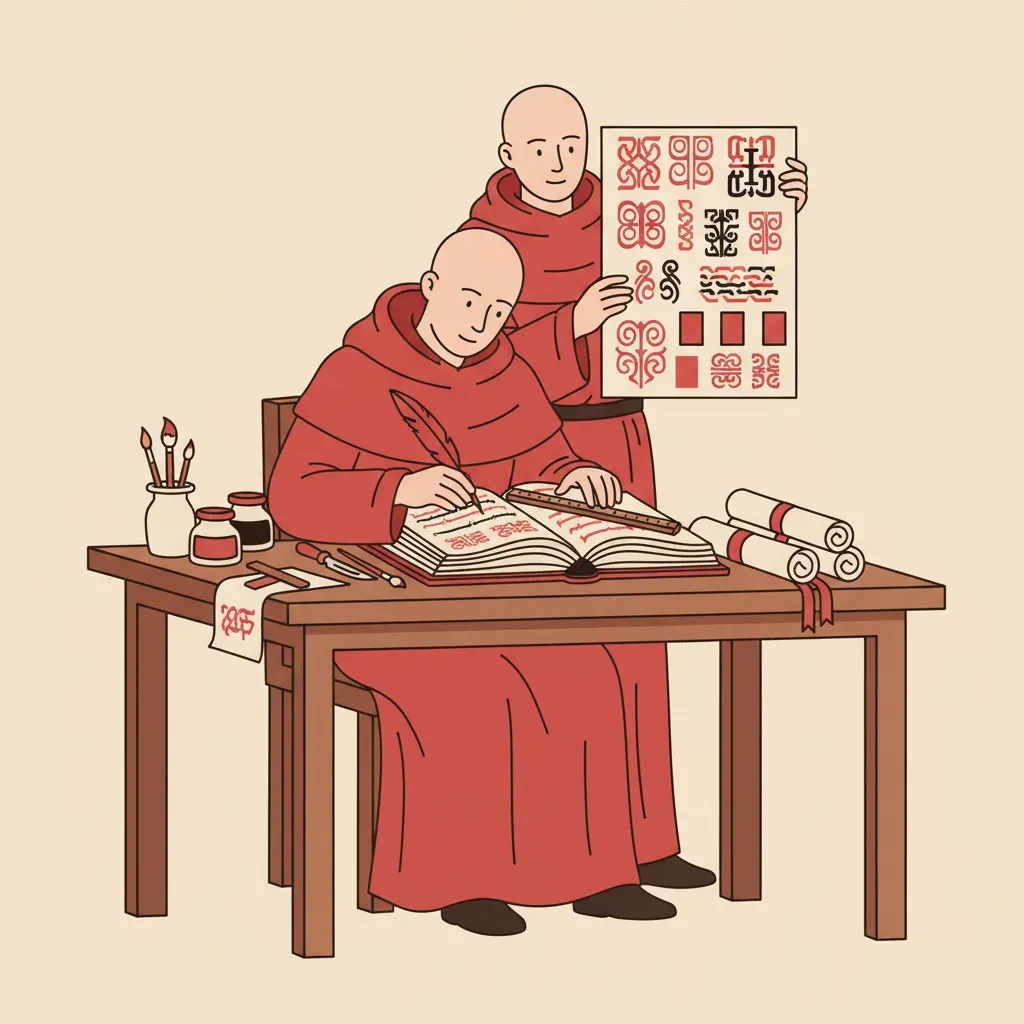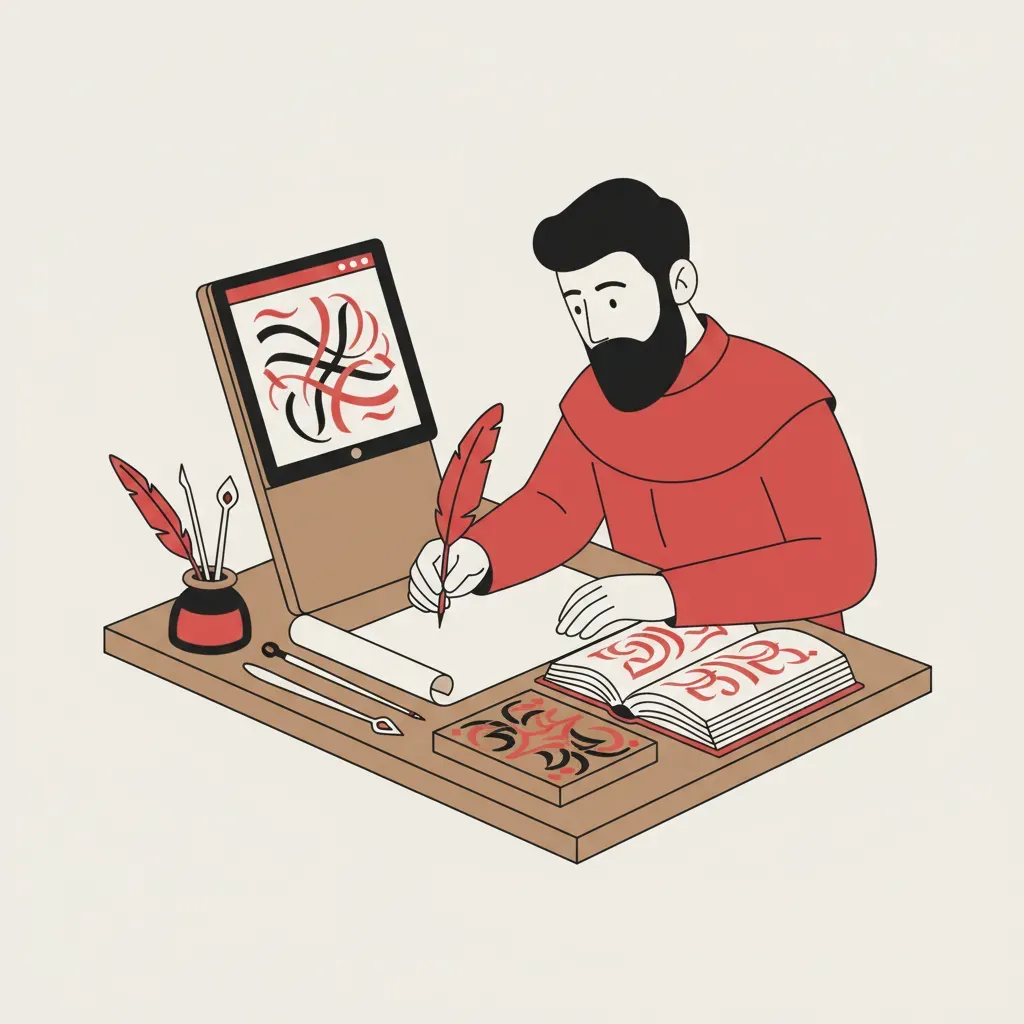
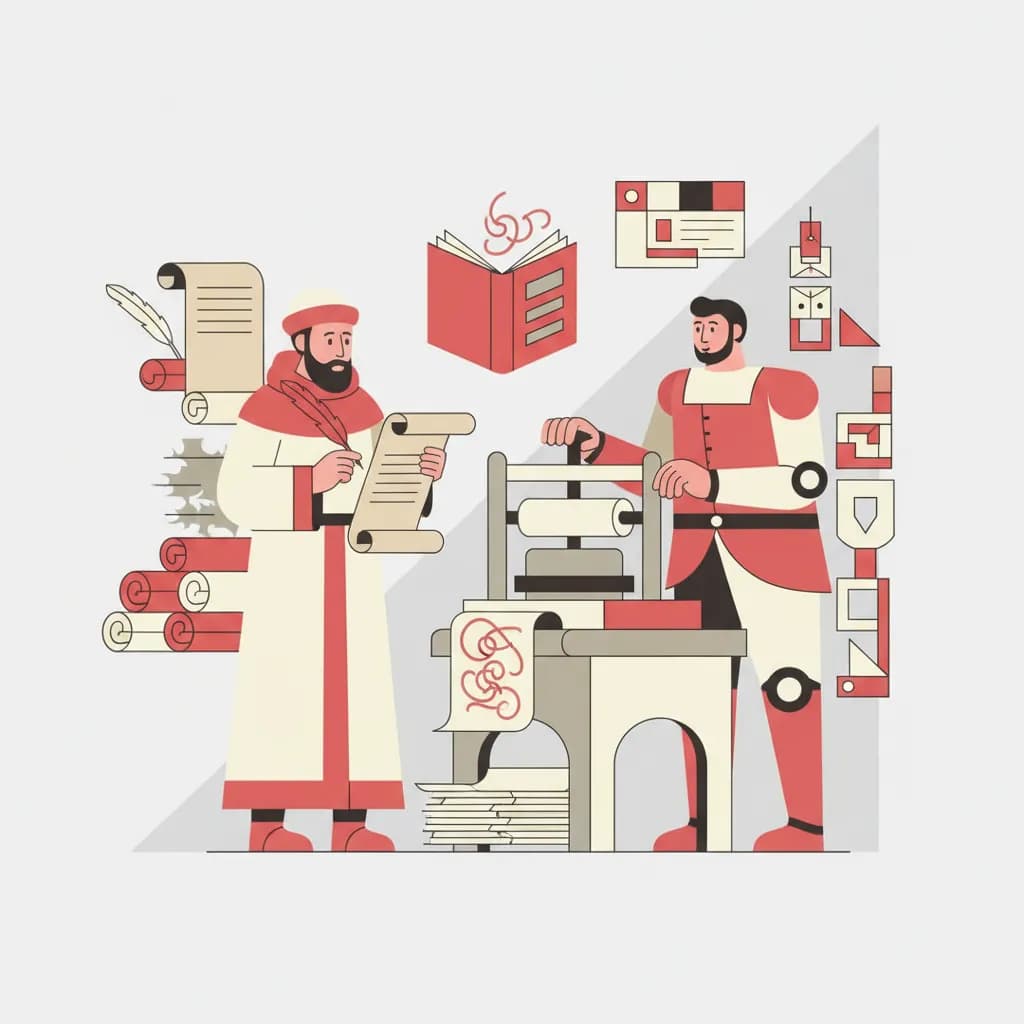
לפני שהיה "שלח לי PDF", לפני שהיה Ctrl+Z, ולפני שמישהו התלונן שפונט נטען לאט באתר – העולם נשען על אנשים שישבו שעות מול קלף, נוצה ודיו, והעתיקו כל אות ביד. בימי הביניים, כתב לא היה רק דרך להעביר מידע. הוא היה כוח. דת. מעמד. שליטה. ולפעמים גם נשק. ימי הביניים – התקופה שנמשכה בערך מהמאה החמישית עד המאה החמש-עשרה – הותירו חותם עמוק על אסתטיקת הכתב שאנו מכירים עד היום.
נקודות מפתח:
היום ספר נוצר בלחיצת כפתור. במאה ה-12, יצירת ספר ידנית הייתה תהליך מאומץ וארוך. נזירים ישבו בחדרים שנקראו סקריפטוריום – חללים שקטים במנזרים שבהם העתיקו כתבי יד. הם כתבו על קלף מעור של בעלי חיים, עם דיו שהוכן מחומרים טבעיים כמו פיח, ברזל וצמחים. זהו אחד ממאפייני ימי הביניים שקשה להבין עד כמה הוא היה מאומץ ומייגע.
טעות קטנה? אין "Delete". לפעמים פשוט גירדו את השכבה העליונה של הקלף עם סכין והתחילו מחדש. זה נשמע רומנטי עד שמבינים שהם עשו את זה בחורף, בלי חימום, במשך שעות, בתאורה של נר. הגב נשבר, הידיים קפאו – והאות עדיין הייתה צריכה להיראות מושלמת.
התהליך בימי הביניים כלל כמה שלבים קבועים:
על פי מה שידוע לנו מהיסטוריה של ימי הביניים, יצירת כתב יד מואר בימי הביניים הייתה תהליך מאומץ שכלל עבודות של מספר אמנים. הכתב יד המואר הוא אחד ממורשות ימי הביניים שהגיעה אלינו בשלמותה.
כי כתב היה ייצוג של קדושה וסדר. במיוחד בעולם הנוצרי של ימי הביניים, האות נחשבה כמעט אלוהית. ספרי קודש לא היו "מוצרים" – הם היו חפצים קדושים. לכן השקיעו בהם זהב, איורים, קישוטים וקליגרפיה ברמת דיוק שלא הייתה מביישת מעצב פונטים אובססיבי ב-2026.
האות הראשונה בכל פרק הייתה לפעמים בגובה של חצי עמוד, מלאה בציפורים, דרקונים ודוגמאות גאומטריות. לא כי זה "יפה" – כי זו הייתה דרך להגיד: הטקסט הזה חשוב יותר מהחיים שלך. הטיפוגרפיה של ימי הביניים שידרה היררכיה ויזואלית ברורה, שהיא עיקרון שעדיין עומד בבסיס כל עיצוב גופן עברי מודרני.
אם ראית פעם כתב ימי-ביניימי שנראה חד, צפוף וכמעט מאיים – זה כנראה כתב גותי. הכתב הגותי נולד בערך במאה ה-12 והפך לסמל של אירופה של ימי הביניים המאוחרים. הוא היה אנכי, צפוף ודחוס, עם קווים חדים כמו קתדרלות גותיות שאפיינו את אותה תקופה.
ולמה הוא נראה ככה? כי קלף היה יקר בטירוף. ככל שהאותיות היו צרות יותר – נכנס יותר טקסט בעמוד. כן – גם אז אנשים ניסו לחסוך מקום באחסון. אבל הכתב הגותי של ימי הביניים לא נשאר רק פתרון כלכלי. עם השנים הוא הפך למשהו עמוק יותר – הוא שידר סמכות, מסתורין, פחד ועוצמה.
זו בדיוק הסיבה שגם היום משתמשים באסתטיקה גותית בלוגואים של להקות מטאל, מותגי יוקרה ואפילו קעקועים. האות עצמה עדיין מרגישה "כבדה" – כאילו יש לה עבר. מי שמעוניין לשלב גופנים עתיקים בעיצוב מודרני ימצא שהכתב הגותי הוא נקודת מוצא מצוינת – בתנאי שמבינים את ההקשר ההיסטורי שמאחוריו.
סגנון כתב תקופה בימי הביניים מאפיין עיקרי שימוש היום קרולינגי מאה 8-12 עגול, קריא, אחיד בסיס לפונטים קלאסיים גותי מאה 12-15 צפוף, חד, דרמטי מטאל, יוקרה, קעקועים אונציאלי מאה 4-8 עגול, גדול, ייצוגי לוגואים, כותרותאחד הדברים הכי מטורפים להבין על ימי הביניים הוא שרוב האנשים בכלל לא ידעו לקרוא. כתב היה שייך לאליטה: נזירים, מלכים, אנשי דת וסופרים מקצועיים. אם ידעת לקרוא ולכתוב – היה לך כוח אמיתי. יכולת לשלוט בחוקים, בדת, במסים, בהיסטוריה.
מי ששלט בטקסט, שלט בנרטיב. רוב האנשים חיו בעולם שבו האמת הייתה מה שמישהו אחר הקריא להם. זהו אחד ההיבטים החשובים ביותר להבנת ימי הביניים: הכתב לא היה רק כלי תקשורת – הוא היה מנגנון כוח ממשי. בימי הביניים, גישה לידע כתוב הייתה מוגבלת ו
הדינמיקה הזו מסבירה גם למה ספרי קודש עוצבו כך שישרו יראת כבוד – לא רק מסיבות אמנותיות, אלא מסיבות פוליטיות. ספר שנראה אלוהי מחזק את הסמכות של מי שמחזיק בו. ההשקעה הגרפית בימי הביניים הייתה, בסופו של דבר, השקעה בשמירת הכוח.
אסתטיקת ימי הביניים חוזרת לאופנה בעיצוב גרפי – אך לעיתים קרובות מיושמת בצורה שגויה. הנה הטעויות הנפוצות ביותר:
הכתב הגותי של ימי הביניים נושא משמעות רגשית כבדה – סמכות, חומרה, עתיקות. שימוש בו על מוצר קליל או ילדותי יוצר ניגוד שמבלבל את הצופה. לפני שמשלבים אסתטיקת ימי הביניים בעיצוב, שאלו: האם הרגש שהסגנון הזה מעביר תואם למסר?
ימי הביניים נמשכו כאלף שנה וכללו עשרות סגנונות כתב שונים – קרולינגי, אונציאלי, רומנסק ועוד. ההכללה "כתב ימי הביניים = גותי" מחמיצה עושר טיפוגרפי עצום. מעצב שמכיר את ההיסטוריה המלאה יכול לבחור את הסגנון הנכון לפרויקט הנכון.
הסופרים של ימי הביניים לא צייר סתם "אותיות יפות" – הם הכירו עקרונות מדויקים של זווית הנוצה, עובי הקו ויחסי הפרופורציות. מי שמנסה לחקות את הסגנון ללא הבנת הבסיס יקבל תוצאה שנראית "בערך גותית" אבל חסרת האיכות האמיתית. כדאי לעיין בעיצוב גופן עברי כדי להבין כיצד עקרונות היסטוריים מיושמים בטיפוגרפיה מודרנית.
במאה ה-15 הגיע יוהאן גוטנברג עם מכונת הדפוס. מה שפעם דרש חודשים של העתקה ידנית הפך למשהו שאפשר לשכפל שוב ושוב. זו לא הייתה רק מהפכה טכנולוגית – זו הייתה קריסה של עולם שלם שבנה את עצמו סביב הנדירות של הכתב.
פתאום ידע התחיל לזוז מהר. ספרים נהיו זולים יותר. אנשים התחילו לקרוא לבד. השליטה של הכנסייה על מידע התחילה להיסדק. אבל – והקטע הכי אירוני – הטיפוגרפיה הראשונה של גוטנברג ניסתה לחקות בדיוק את הכתב הגותי של הסופרים הידניים מימי הביניים. הדפוס החדש התחפש לישן כדי שאנשים יסמכו עליו.
זהו לקח שרלוונטי גם כיום: כשטכנולוגיה חדשה מגיעה, היא לעיתים קרובות לובשת את הצורה של הישנה. גם פונטים דיגיטליים מודרניים – כולל אלה שאפשר למצוא בGoogle Fonts – לעיתים שואבים השראה ישירה מסגנונות ימי הביניים, ומתרגמים אותם לפורמטים שמתאימים לעיצוב דיגיטלי עכשווי.
בסופו של דבר, ימי הביניים לא נגמרו באמת – הם חיים בכל פונט שמעצבים, בכל הזמנה שמודפסת, ובכל לוגו שמשדר עומק ועוצמה. הטכנולוגיה השתנתה, אבל הרגש שאנשים מחפשים בצורת האות נשאר זהה לחלוטין.